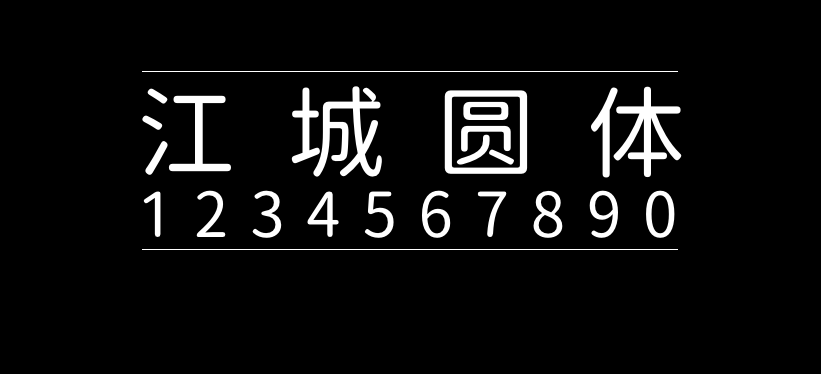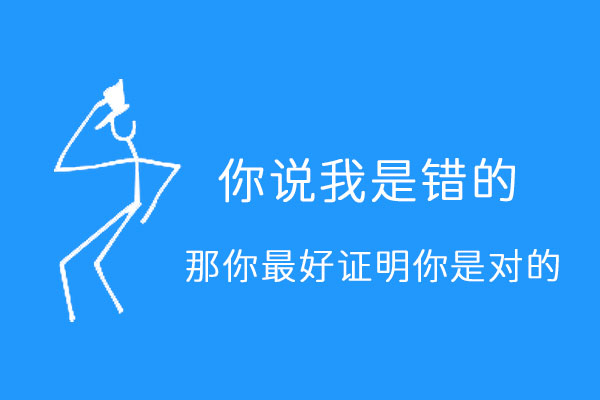
江城圆体
自由君在收集免费商用字体的过程中,一直觉得没有一款比较好的圆润中文字形,国内大部分都介绍使用“思源柔黑体”,也就是源柔黑体(日本自家製フォント工房改造的思源字体),以及一款是源泉圆体,但是这款字体对于中国大陆的设计师来说依然有点小瑕疵。源泉圆体因为是台湾设计师改造的字体,所以字形上会更贴近中国台湾的使用习惯。
终于国内一位被设计耽误的程序大神刘鹏,基于源泉圆体进行改造,把一些台湾习惯的字形进行简体化修正,发布了一款比较适合我们大陆设计师使用的字体“江城圆体”。这款字体基本源泉圆体改造,所以简体字符比较全,并且有6个字重,十分贴心。